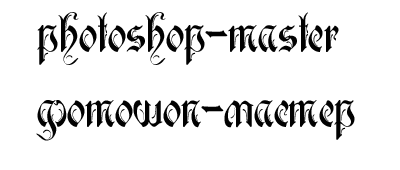
Шрифт - Rurintania
Интересный шрифт, который хорошо подходит для работы в фотошопе. Есть поддержка русского языка.
Внешний вид:
я в восторге!
Какой красивый шрифт!!! Спа-си-бо!!!
о_о Потрясающе! Очень нравится =) Спасибо!
Спасибо! Отличный шрифт,очень нужный.
Красиво- ок
Огромное спасибо!Очень красиво!!!
Прикольно! Мне понравился! =)
прекрастный шрифт!
Офигеть мне понравились, спасибо!:)
Отличный шрифт!!!!
Просто сказка! Класс!
пригодится такой классный шрифт
офигенный шрифт
красиво=)